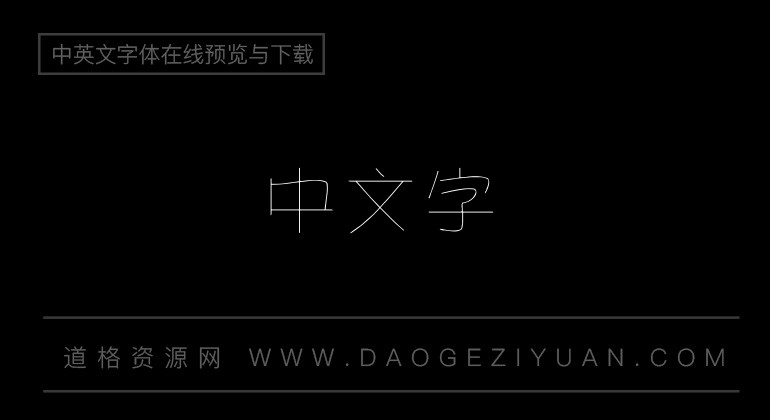
金梅美工钢笔细字
金梅美工钢笔细字是一款钢笔字体,它采用精致的细笔触,具有极佳的精细度和细节性,适用于文字设计、标识设计、书法等领域。它的笔画细腻,线条精细,可以清晰地表达出文字的内容,使文字具有精美的外观。它还具有优质的稳定性,可以保持文字的精确度,使文字看起来更加精致。
金梅美工钢笔细字是一款非常不错的手写艺术字体,具有很好的视觉感,适合于文化类的宣传设计、商业类品牌的广告和产品包装设计以及个性化文字排版等较多场景。